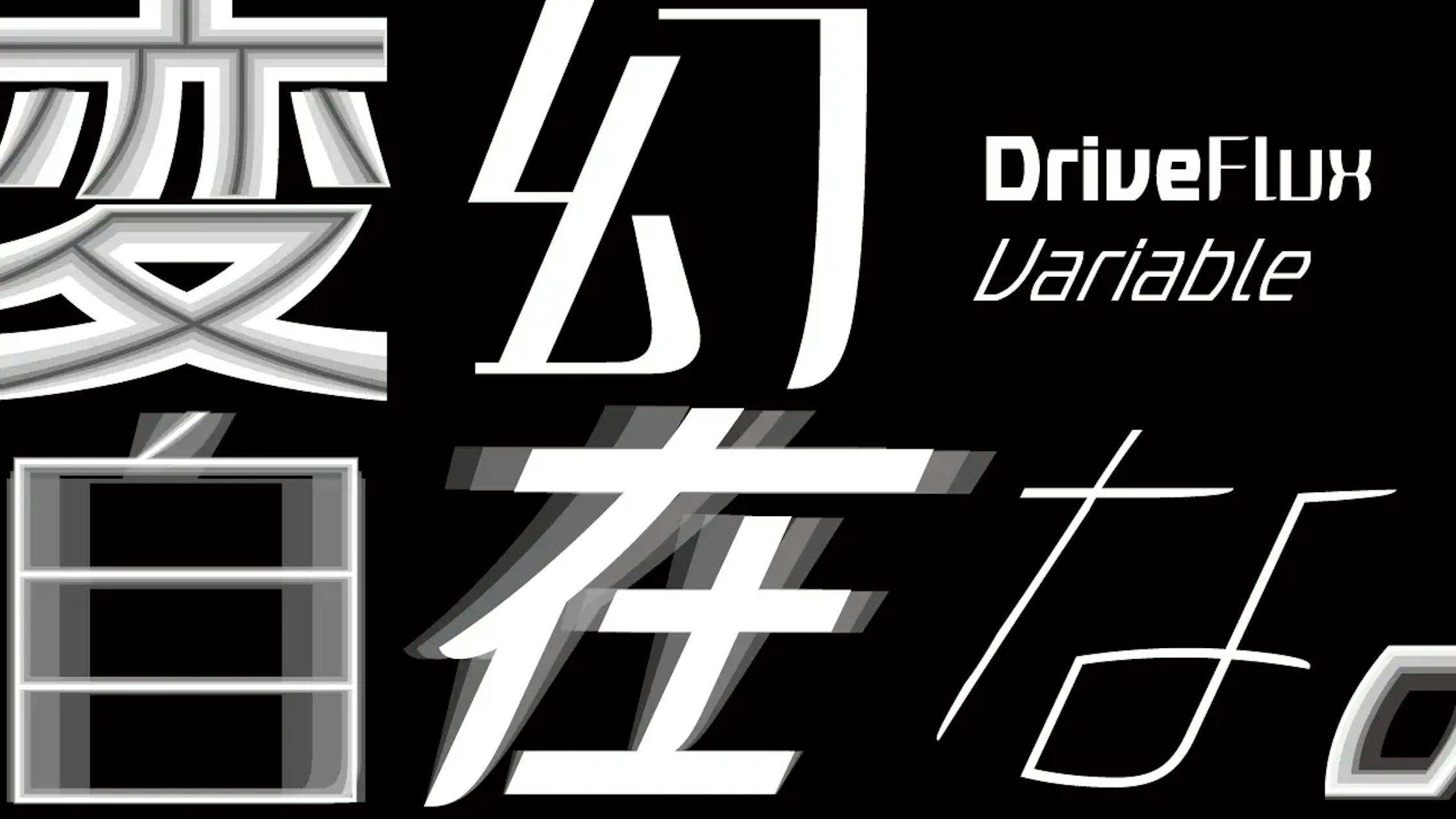
モリサワ、同社初の和文バリアブルフォント『DriveFlux』を発表
モリサワは、同社初となる和文バリアブルフォント「DriveFlux(仮称)」を2024年度中に提供予定であると発表しました。
DriveFluxは新たにデザインされたバリアブルフォントで、シンプルでシンメトリーな骨格と幾何学的なストロークから成っています。また、デザインバリエーションが豊富で、選択が直感的かつシームレスとなる可変機能を備えており、見出しや目を引きたいシーンに適しているとのことです。
バリアブルフォントは、従来ウェイトや字幅ごとにフォントファイルが必要だったものを1つのファイルに集約し、軽量で柔軟なスタイル選択を可能とする次世代のフォントフォーマットです。DriveFluxは、「Drive your Design. Drive your Typeface.」をコンセプトに展開され、以下の4つの可変軸があります。
• 太さを調節するWeight(ウェイト)軸
• エレメントに流線型のカーブデザインを与えるSmoothness(スムースネス)軸
• 主に横画の太さを変化させるContrast(コントラスト)軸
• 傾斜角を調節するSlant(スラント)軸